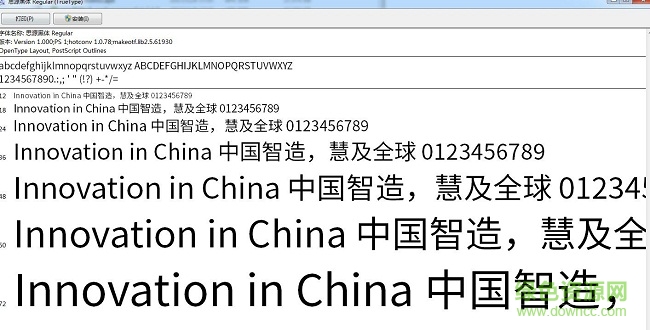
sourcehansanssc regular字體
sourcehansanssc regular字體是一款大方優(yōu)雅的黑體字體,黑白勻稱,線條流暢,實(shí)用性強(qiáng),不論是廣告、平面設(shè)計(jì)等領(lǐng)域都可以使用,支持手機(jī)、平板、電腦,歡迎大家免費(fèi)下載!
sourcehansanssc字體